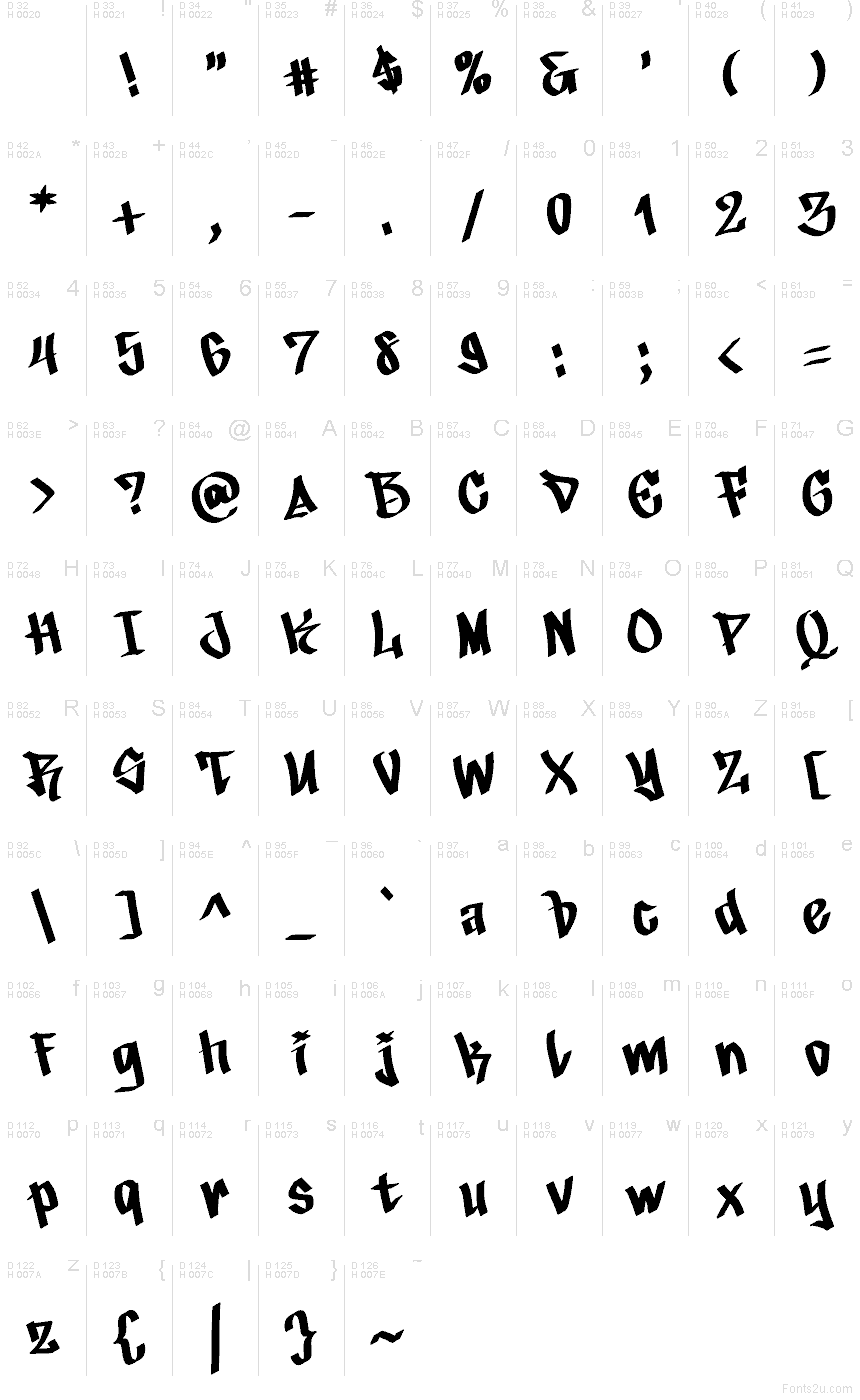
Street Bring
Street Bring est une police graffiti gratuite aux formes tranchantes et anguleuses, avec des courbes fluides tracées à la main qui rappellent l'art de la rue au pochoir. Les lettres sont ciselées en coupes pointues et formes inclinées, aux bords irréguliers, créant un rythme brut et plein d'énergie.
Cette police gratuite est parfaite pour les titres d'affiches, les pochettes d'albums, les visuels de skate, le branding streetwear et les logos recherchant une touche urbaine. Street Bring convient également aux illustrations de couverture, aux flyers d'événements et aux accroches percutantes où un style graffiti brut suffit à porter tout le design sans décoration superflue.